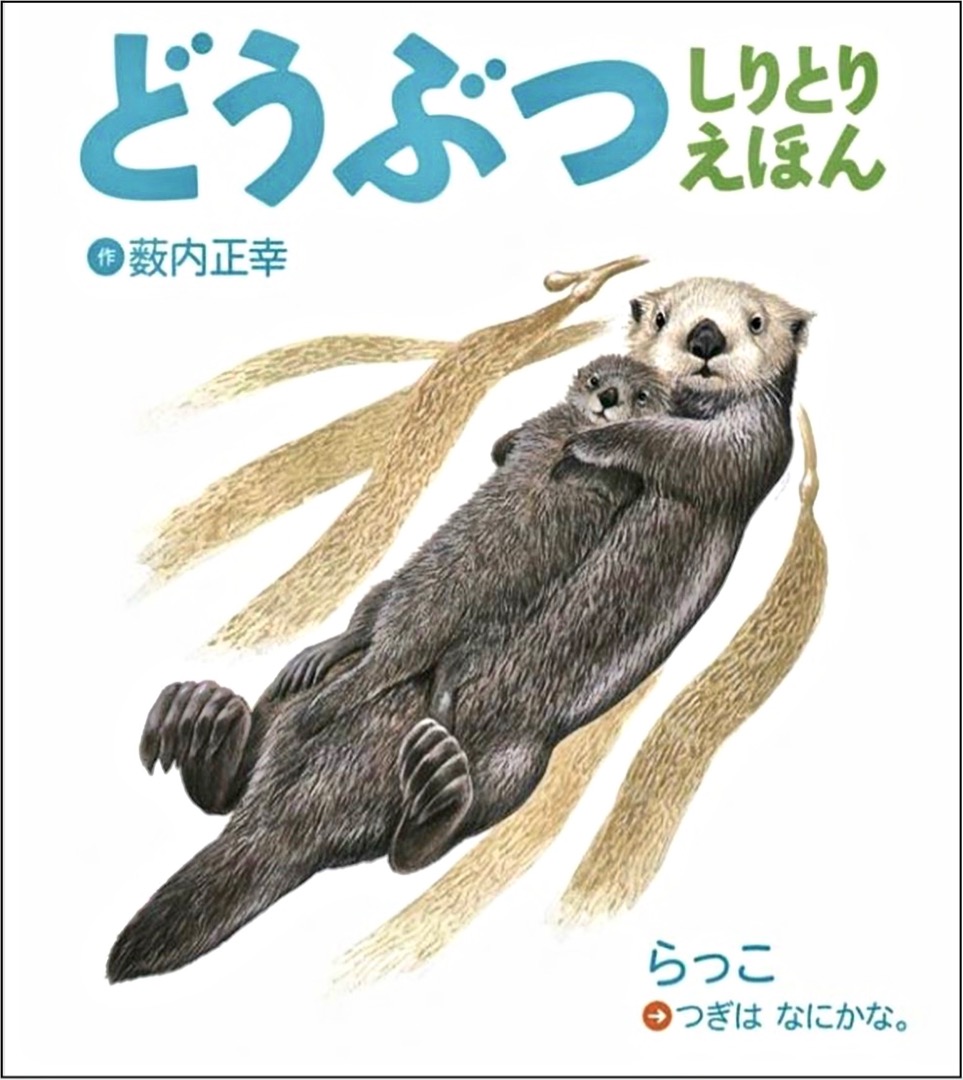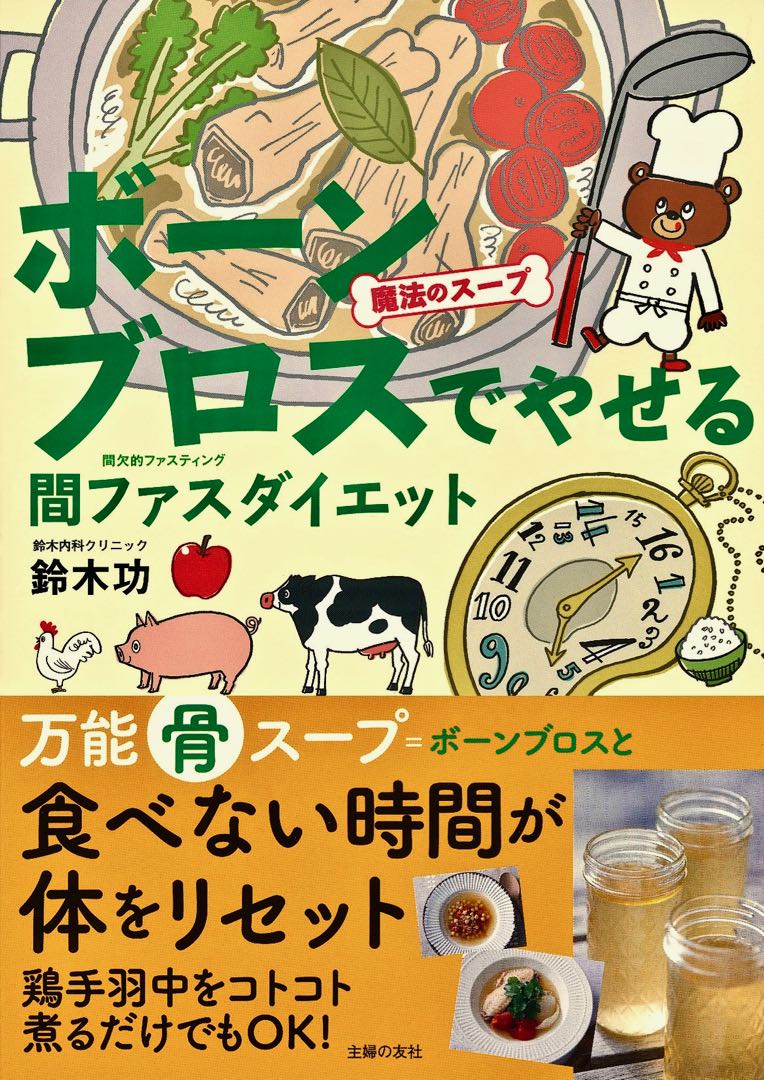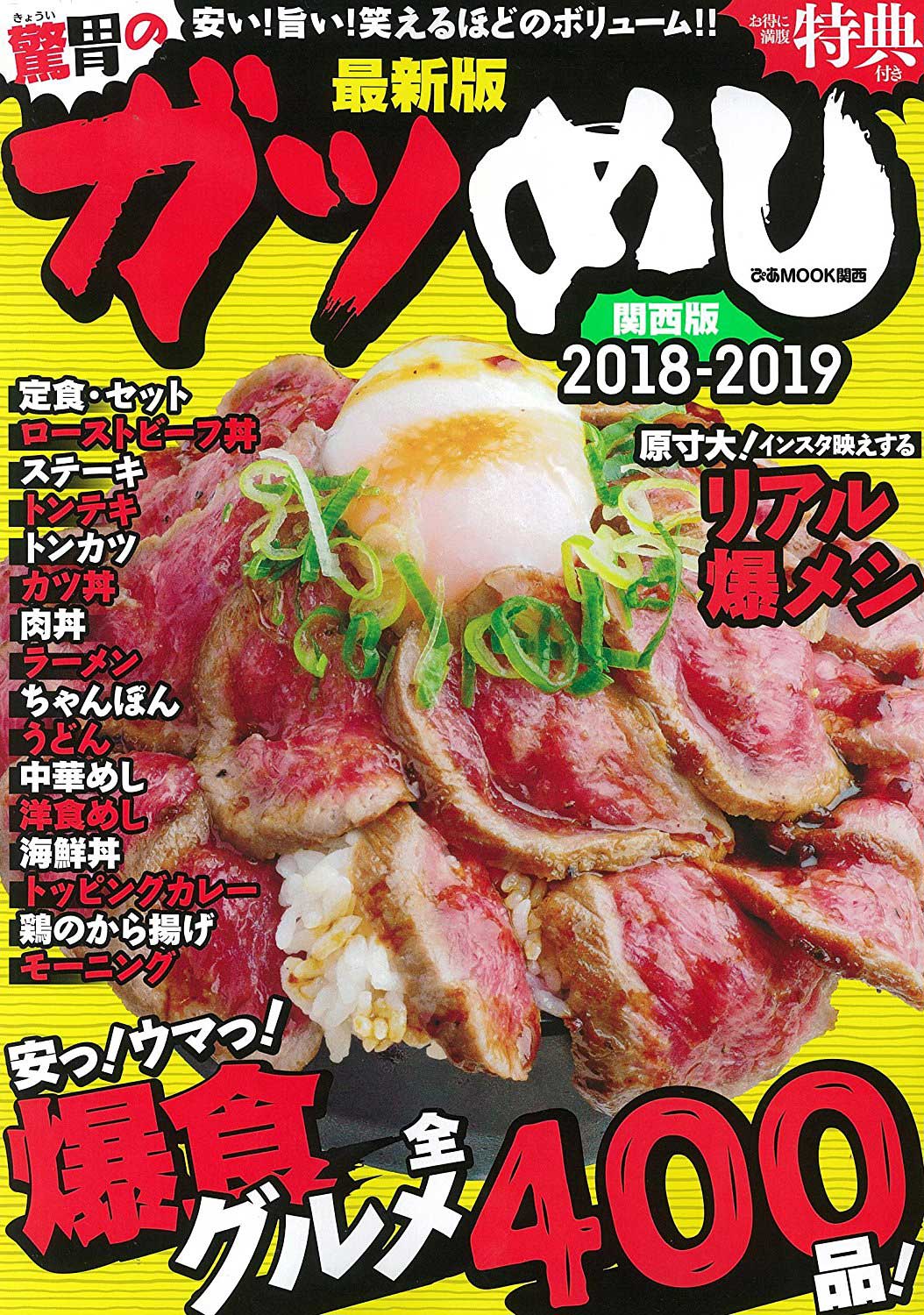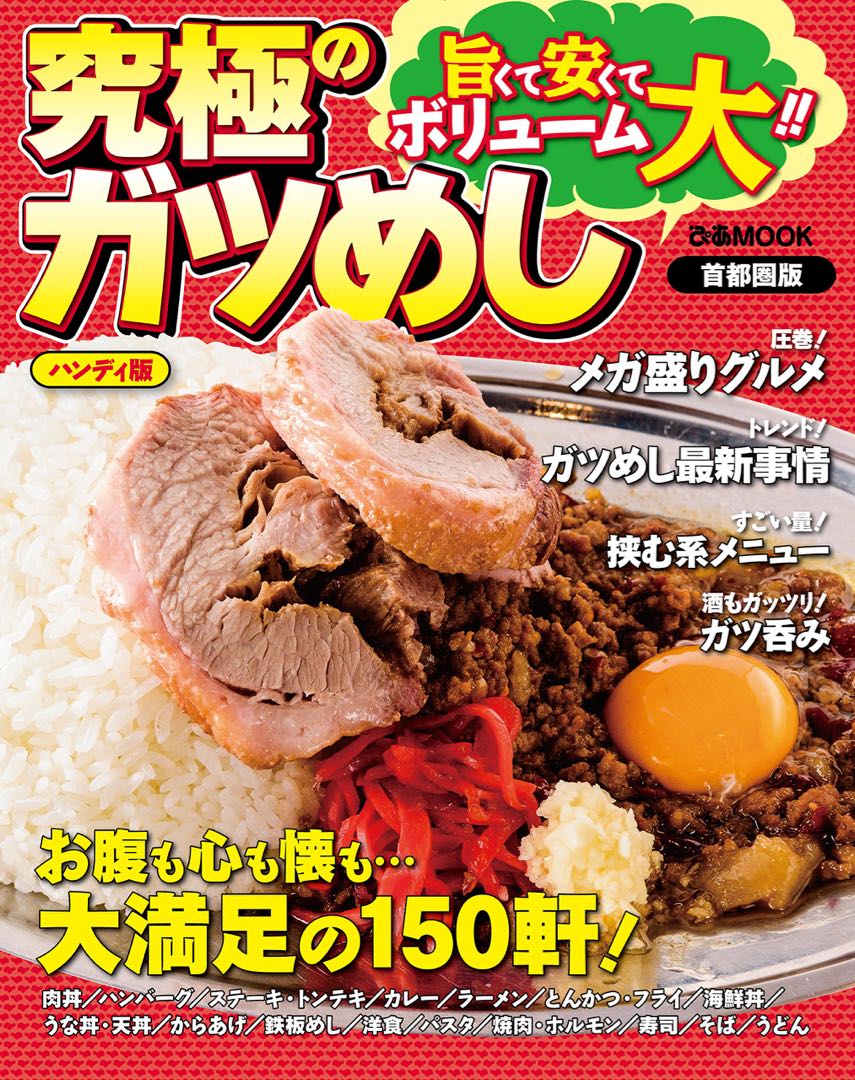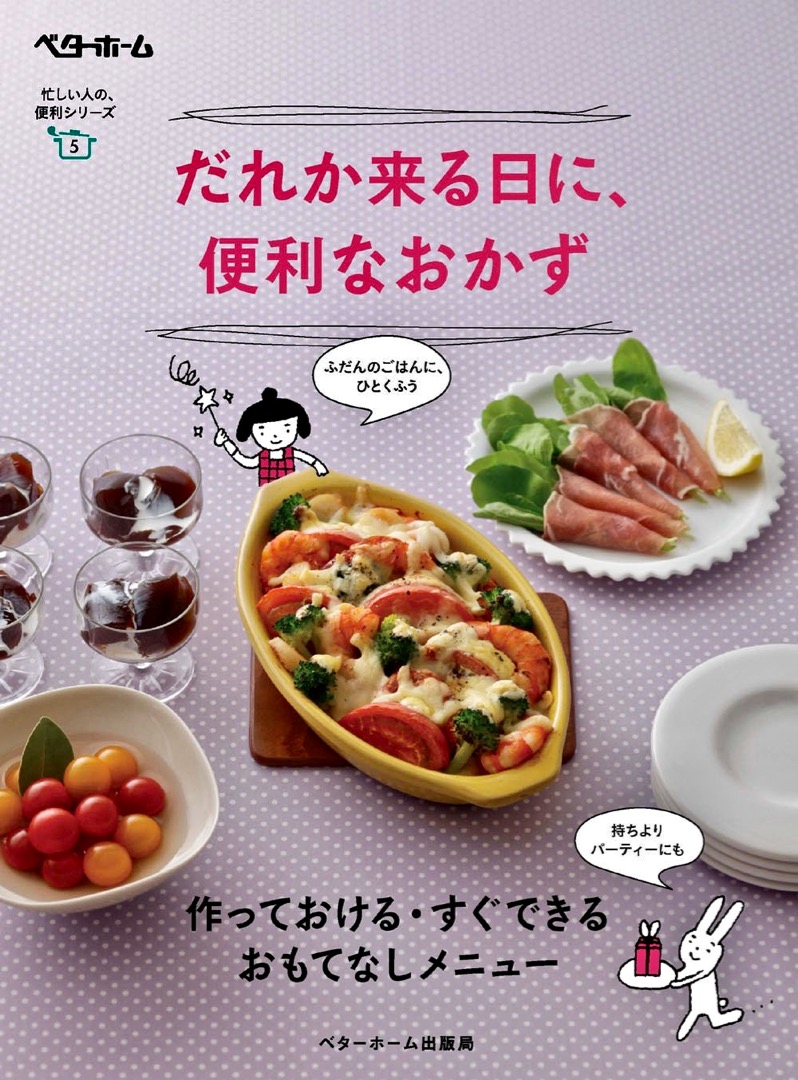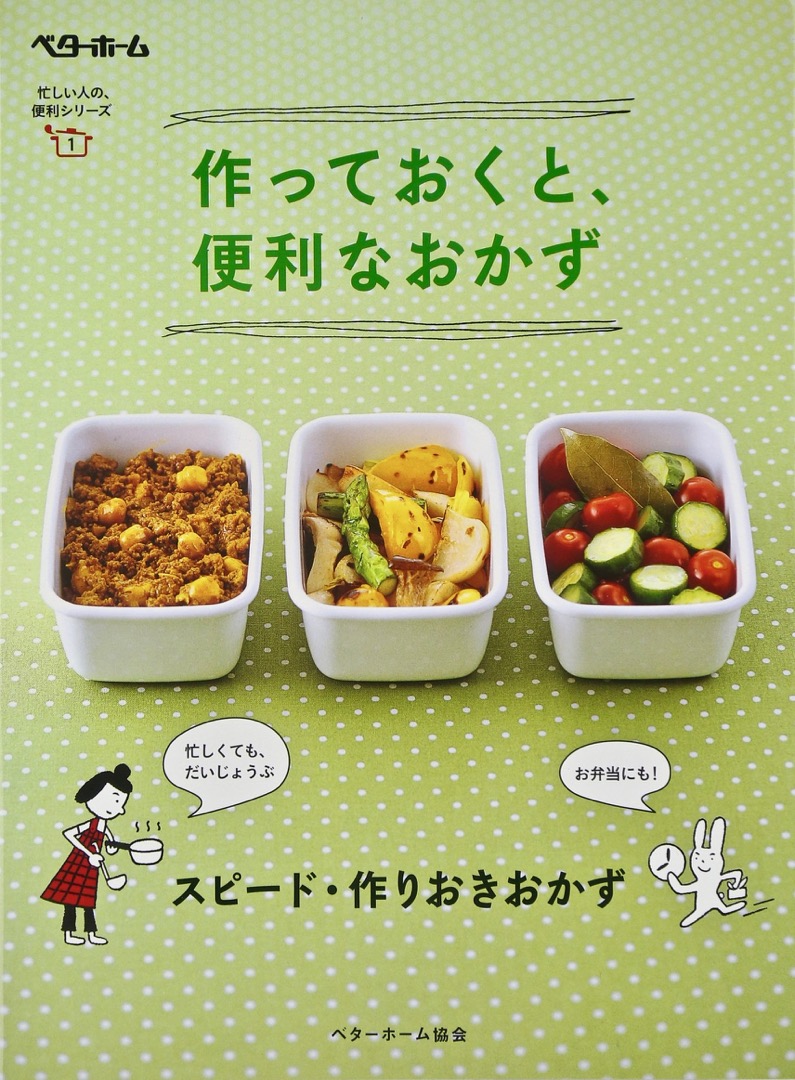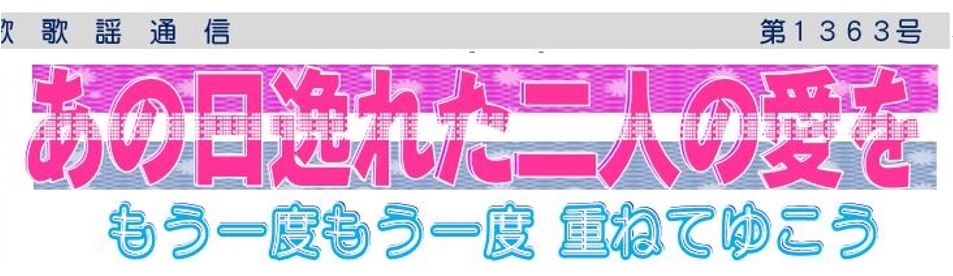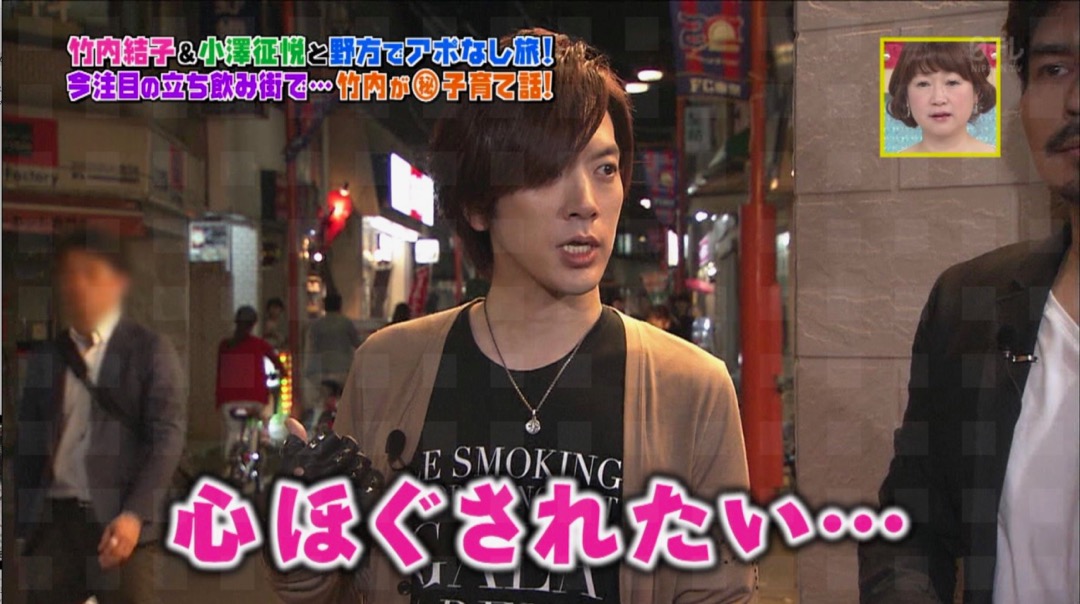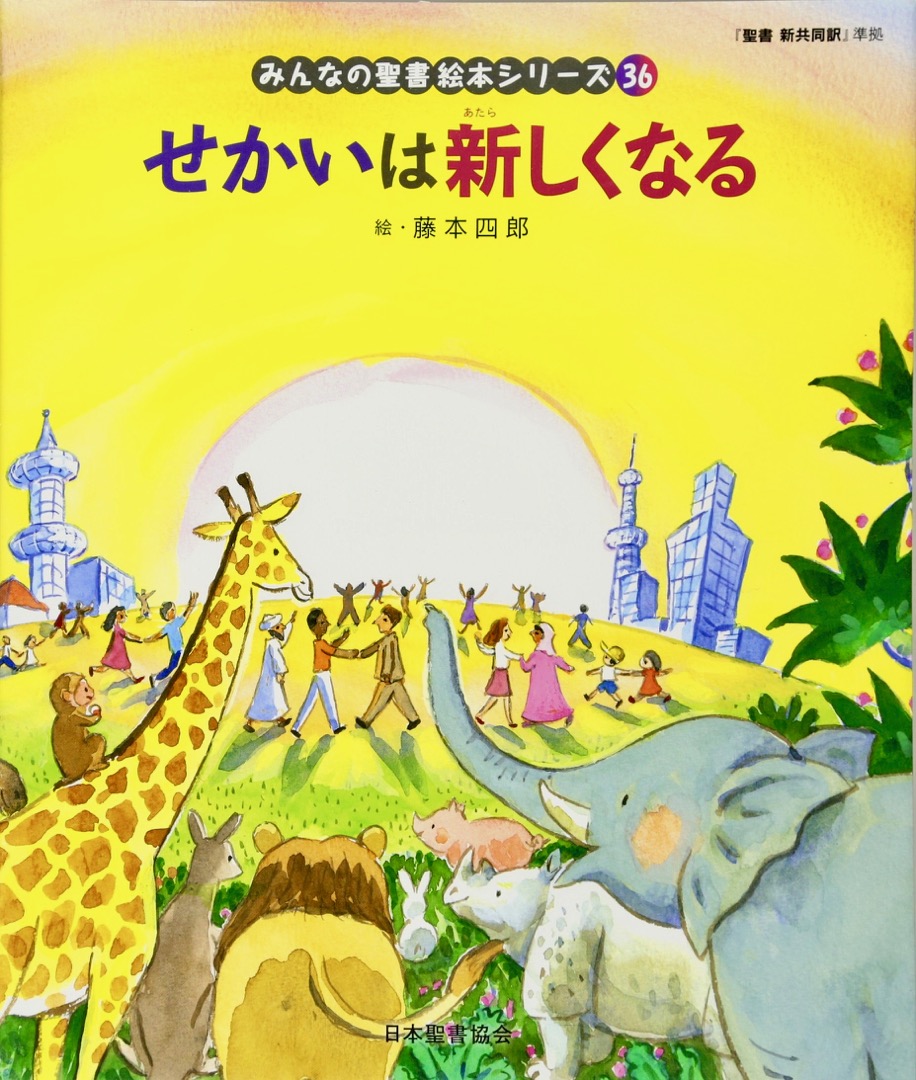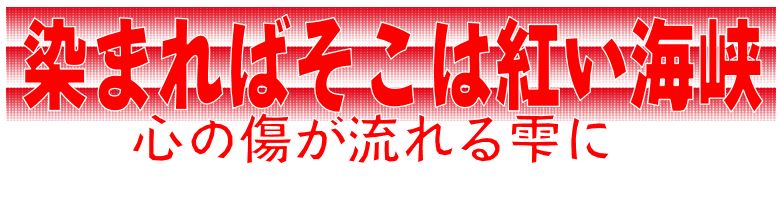
雑誌の表紙  さとうゆたか  2019年6月27日(木) 16:44
タテに組まれた「わちみなみ」の部分。
書名:ヤングキングブル
発行:少年画報社
本の表紙  さとうゆたか  2019年6月16日(日) 8:39
書名:納豆でやりくりレシピ
著者:学研
発行:学研
ビアガーデン広告  さとうゆたか  2019年6月7日(金) 14:56
東武スカイツリー線に乗ると、目にするポスター。
テレビ番組  さとうゆたか  2019年5月22日(水) 10:40
NHKで毎日午前中に放送されている『ひるまえ ほっと』。
もう1点。
まだあった…。
新聞広告  さとうゆたか  2019年5月1日(水) 9:26
今朝の読売新聞、2ページ使った広告。
手でトレスして描いたように加工されている。
リケンは、WEBサイトでも墨東書体のトレス風を使っているようだ。
本の表紙  さとうゆたか  2019年4月24日(水) 17:19
書名:魔法のラーメン発明物語
著者:安藤百福
発行:日本経済新聞出版社
WEBフォント  さとうゆたか  2019年4月3日(水) 17:15
墨東ルイカで表示されるオロナイン軟膏のサイト。
フォントストリームのWEBフォントサービスを使っている。
←この画像と文字の組み合わせは、スマホじゃないと見えないようだ。
新聞広告  さとうゆたか  2019年2月27日(水) 9:33
数日前に見た広告。
WEB画像  さとうゆたか  2019年2月14日(木) 17:06
琉球泡盛 八重泉酒造のサイト。
NHKみんなで筋肉体操(2019年1月放送ぶん)  てなしも  2019年1月15日(火) 19:03  HP
2019年に放送された「みんなで筋肉体操(第二シーズン)」4本の番組中テロップ「準備はいいですか?」「あと少しがんばりましょう」に墨東ルイカが使用されています。
またBS1不定期放送のNHK「世界ふれあい町歩き」「世界入りにくい居酒屋」の吹き替えキャプションで見かけることも多くなりました。
これですね。
もう1点。
墨東ルイカではなく、他社にライセンスされた墨東のようです。